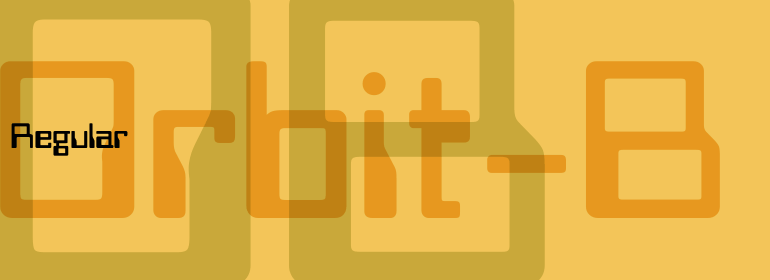
Orbit-B
Orbit-B,这款字体结构工整、笔画清晰,兼顾美观与易读性,适用于标题、正文、海报、包装、LOGO 等多种场景。字形优雅稳定,风格百搭耐看,适配日常排版与创意设计,让文字呈现更舒适、更具质感。Orbit-B一笔一画,皆是细节,以均衡的比例、流畅的线条打造舒适视觉体验,字形端正大气,风格简约现代。无论是商业设计、品牌宣传还是日常排版,都能轻松驾驭,让文字更有格调与力量。Orbit-B字体下载。